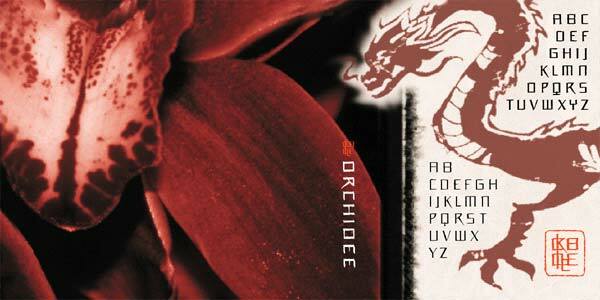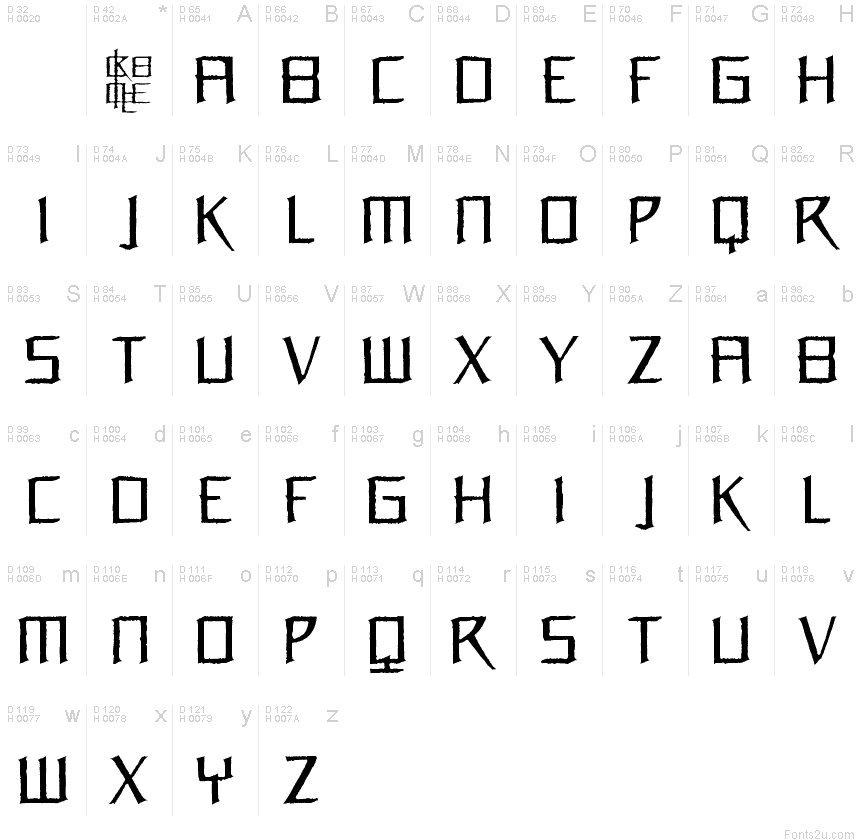
Orchidee to darmowy, erodowany krój pisma o ostrych, nieregularnych pociągnięciach i szorstkich krawędziach, które nadają literom surową, wycinaną ręcznie teksturę. Jego formy są wąskie i kanciaste, z wysokimi pionami, spiczastymi zwrotami i drobnymi, nieregularnymi pęknięciami, co tworzy napięty, wyrazisty rytm.
Orchidee świetnie sprawdzi się na plakatach, okładkach albumów, w horrorowych tytułach, ulotkach eventowych oraz w brandingu wymagającym podrapanego lub postarzanego efektu. Ten darmowy font pasuje również do grafiki gier, opakowań i dekoracyjnych logo, gdzie jego ząbkowany kontur dodaje szorstkiego akcentu bez potrzeby dodatkowych szczegółów.